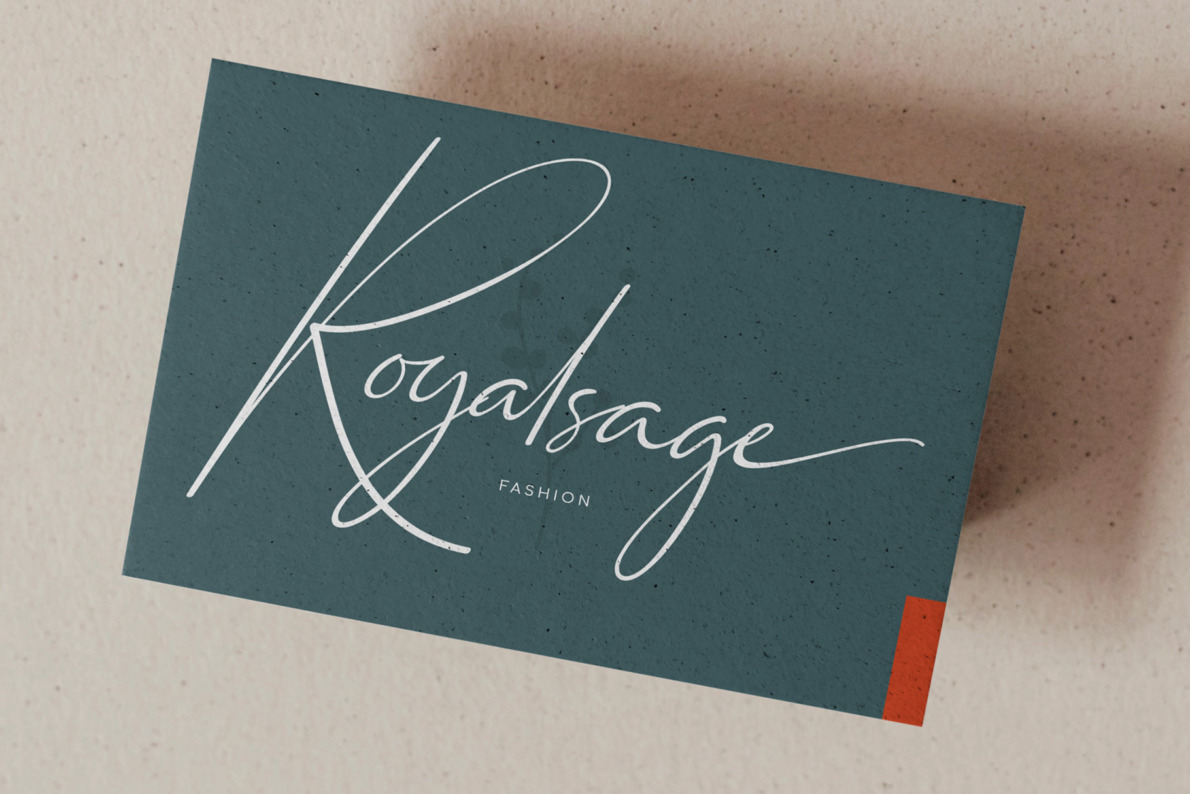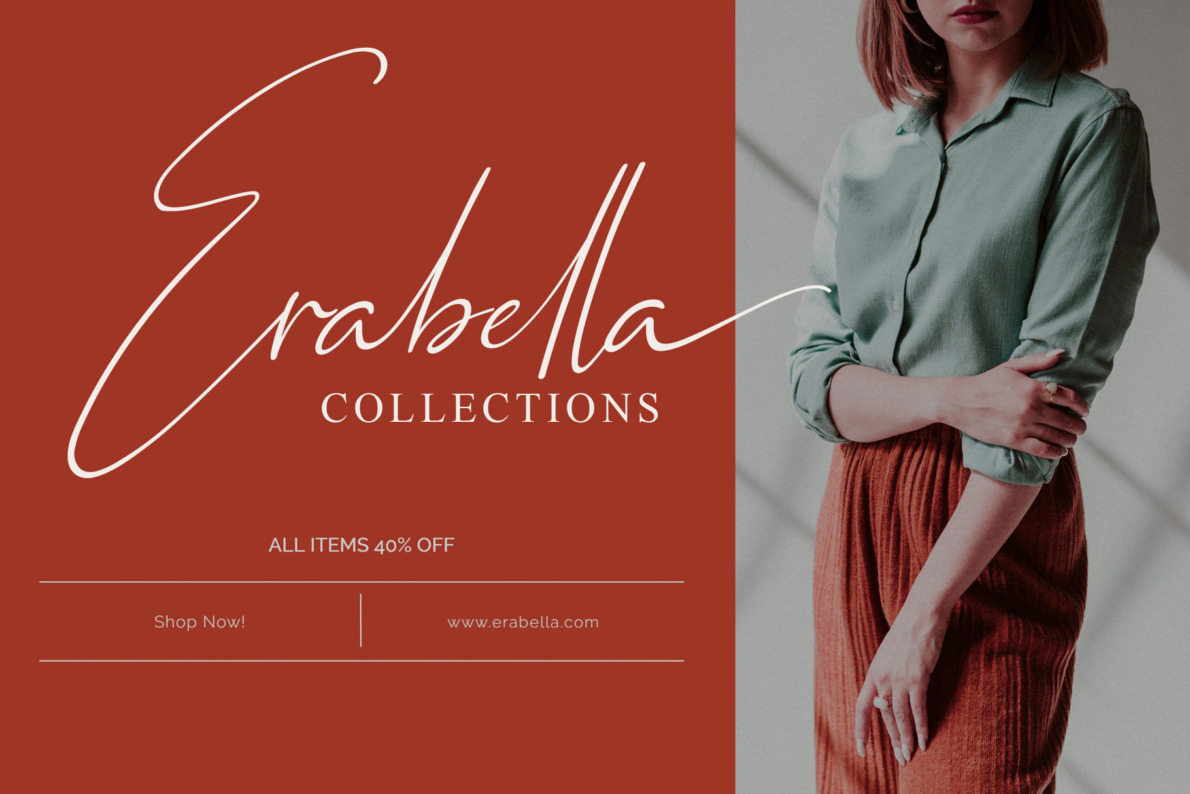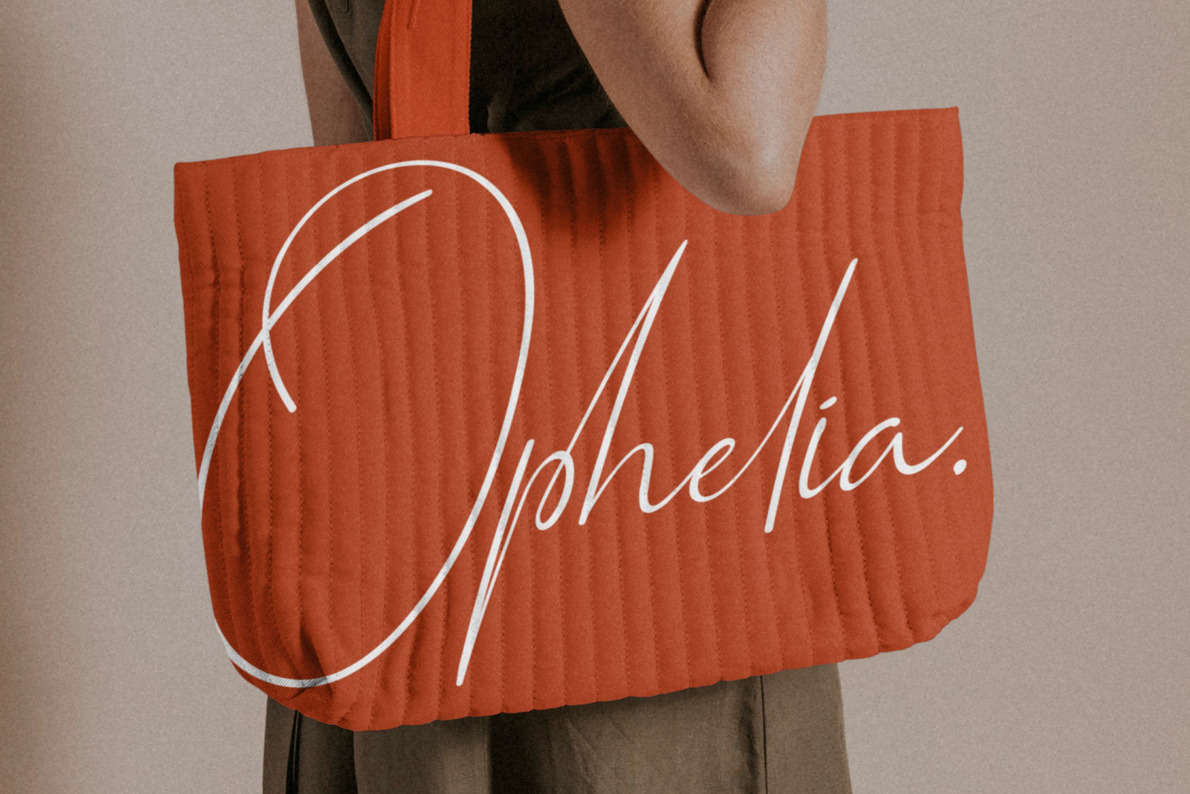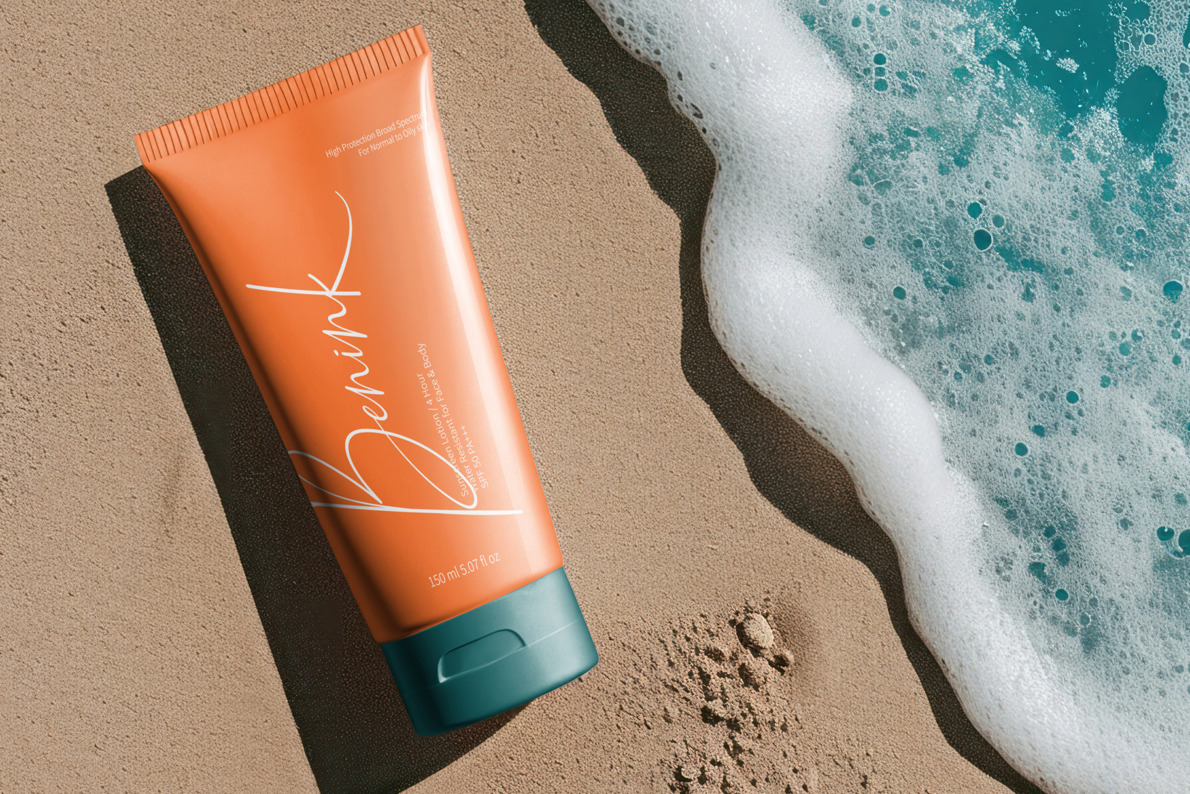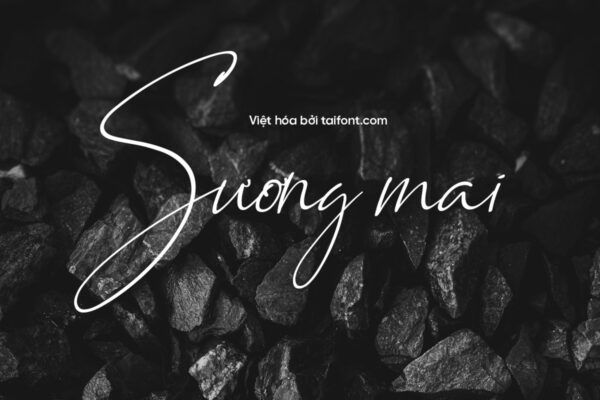
Giới thiệu về Font TF Monoluxe Việt hóa
TF Monoluxe Việt hóa là một font chữ viết tay (script font) nổi bật với thiết kế dáng cao, thanh mảnh và đầy sang trọng, mang đến vẻ đẹp tinh tế, hiện đại và một chút bay bổng. Font này gợi cảm giác như một chữ ký được viết tay một cách tỉ mỉ, có hồn, tạo nên sự độc đáo và riêng biệt cho mọi thiết kế. Sự kết hợp giữa nét cao thanh lịch và sự uyển chuyển làm cho Monoluxe trở nên rất cuốn hút.
Với sự duyên dáng và tính thẩm mỹ cao, Monoluxe là lựa chọn lý tưởng cho các thiết kế muốn truyền tải sự tinh tế, cá nhân hóa và một chút nghệ thuật:
- Thiết kế thời trang: Hoàn hảo cho các thương hiệu thời trang cao cấp, từ logo, nhãn mác sản phẩm, lookbook, đến các chiến dịch quảng bá bộ sưu tập. Font này giúp truyền tải vẻ đẹp thanh lịch, đẳng cấp và độc đáo của trang phục, nâng tầm giá trị thương hiệu.
- Các chữ cảm hứng lên ảnh: Lý tưởng để thêm các câu trích dẫn, lời nhắn, chú thích hoặc các đoạn thơ ngắn lên ảnh chụp cá nhân, ảnh phong cảnh, hoặc ảnh đăng trên mạng xã hội. Nét đẹp của Monoluxe sẽ biến những dòng chữ trở nên nghệ thuật, lãng mạn và đầy cảm xúc, giúp bức ảnh của bạn thêm phần nổi bật và có hồn.
- Thiết kế tạp chí và ấn phẩm cao cấp: Phù hợp để sử dụng cho các tiêu đề phụ, lời dẫn, trích dẫn hoặc các bài viết mang tính chất nghệ thuật, văn học trong các tạp chí về thời trang, làm đẹp, hoặc phong cách sống. Font này sẽ làm cho nội dung trở nên sống động, gần gũi và thu hút độc giả.
Với TF Monoluxe Việt hóa, bạn có thể dễ dàng thổi hồn nghệ thuật, sự tinh tế và cá tính vào các thiết kế, tạo ra những sản phẩm không chỉ đẹp mắt mà còn đầy cảm xúc và sức hút đặc biệt.
Font Việt hóa TF Monoluxe – Phong chữ mỹ phẩm thời trang viết tay